Wo Bilder fehlen, übernimmt die Schrift ihre Aufgabe: Sie schmückt, lehrt und erinnert. Verse aus dem Koran, fromme Sprüche und Suren werden in immer neuen Variationen verwoben — auf Pergament, in Stein, auf Stoff und in Holz. Aus Buchstaben werden Ranken, aus Worten ganze Gärten.
Arabische Ornamentik
Die arabische Schrift ist eng mit dem Islam verbunden. Da der Koran bildliche Darstellungen untersagt, wurden in religiösen Texten die Schriftzeichen selbst zum Ornament — die Kalligraphie erlangte so höchsten Wert und größte Anerkennung.
Schrift wird Bild
Vom Gebet zum Ornament
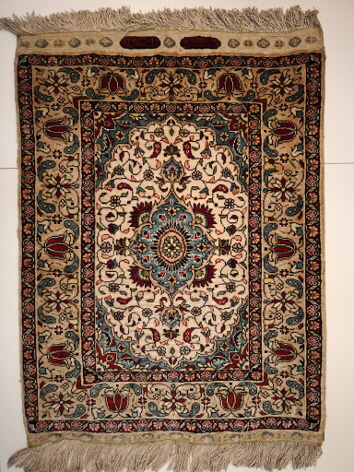
Gebetsteppich
Worte unter den Füßen
Wer den Gebetsteppich ausrollt, breitet ein ganzes Werk der Schrift vor sich aus. Rahmen, Mihrāb und Bordüren tragen Verse und Segenswünsche — fein gewebt, vielfach gespiegelt, aus der Ferne wie ein abstraktes Muster, aus der Nähe lesbar wie ein Buch.
Sure 27 — Die Ameise
Verse, kunstvoll verschlungen
Ein Ausschnitt aus der Sure von der Ameise zeigt, wie sich Inhalt und Form in der arabischen Kalligraphie verbinden. Diakritische Punkte, Bögen und Schwünge sind keine Beigabe — sie sind das Bild selbst, das den Vers in eine Andachtsform überführt.